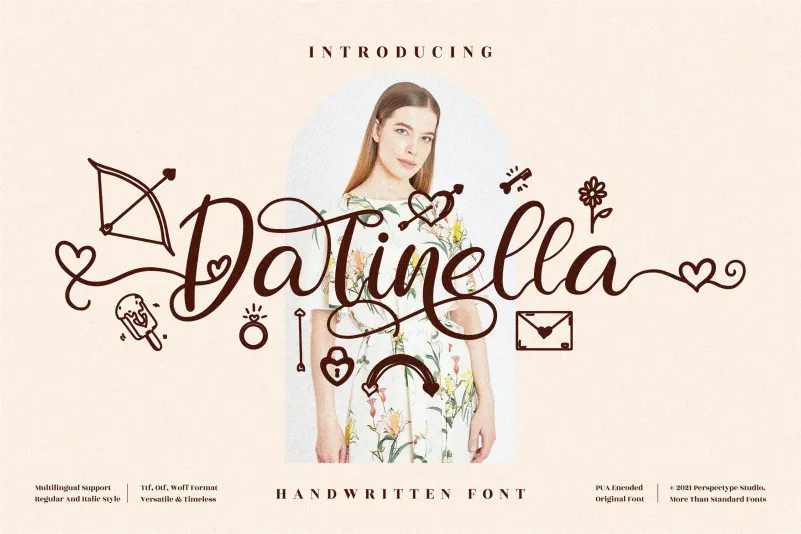
Darinella Font – Download Grátis
Esta é uma tipografia de escrita romântica e suave que traz caracteres dançando ao longo do fundo. A Darinella Font é perfeita para qualquer projeto de design, seja ele complexo ou simples, ela adicionará um toque de luxo e sofisticação. Com todos os seus maravilhosos símbolos e ligaturas PUA codificadas, você pode acessá-los facilmente sem precisar de grandes conhecimentos técnicos. Seja para criar um logotipo elegante ou adicionar uma dose doce ao seu layout de newsletter, a Darinella Font é uma escolha perfeita que certamente adicionará um novo encanto à sua composição gráfica.